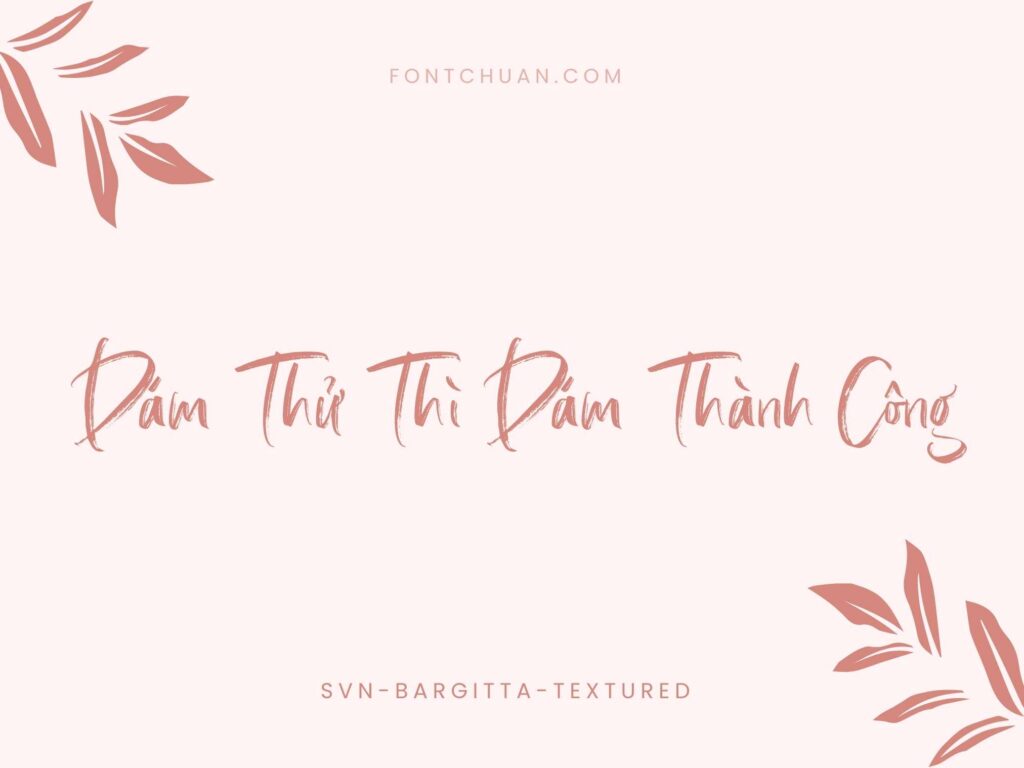
Font SVN Bargitta Textured Việt Hóa
Tác giả Font: Sarid Ezra
Bargitta là một font chữ viết tay hiện đại, được thiết kế bởi Letterhend Studio. Font này mang phong cách tự nhiên và thời trang, hoàn hảo cho các thiết kế sáng tạo. Bargitta có sẵn trong ba phong cách khác nhau: SVG, solid và textured, cung cấp sự linh hoạt cho các nhà thiết kế trong việc tạo ra những tác phẩm độc đáo. Font đã được Việt hóa để hỗ trợ tiếng Việt bởi Styleno.1 Fonts, đồng thời hỗ trợ nhiều ngôn ngữ khác, giúp mở rộng phạm vi sử dụng trên toàn cầu. Font này được thành viên của Font Chuẩn sưu tầm và chia sẻ, đáp ứng nhu cầu của bạn đọc và ứng dụng thực tế vào các dự án thiết kế.
Đặc điểm thiết kế của Bargitta bao gồm các đường nét viết tay tự nhiên, tạo cảm giác chân thực và gần gũi. Font này phù hợp cho các ứng dụng như thiết kế logo, tiêu đề, thiệp mời và các dự án sáng tạo khác. Các ngành nghề phù hợp bao gồm quảng cáo, nghệ thuật và thiết kế đồ họa.